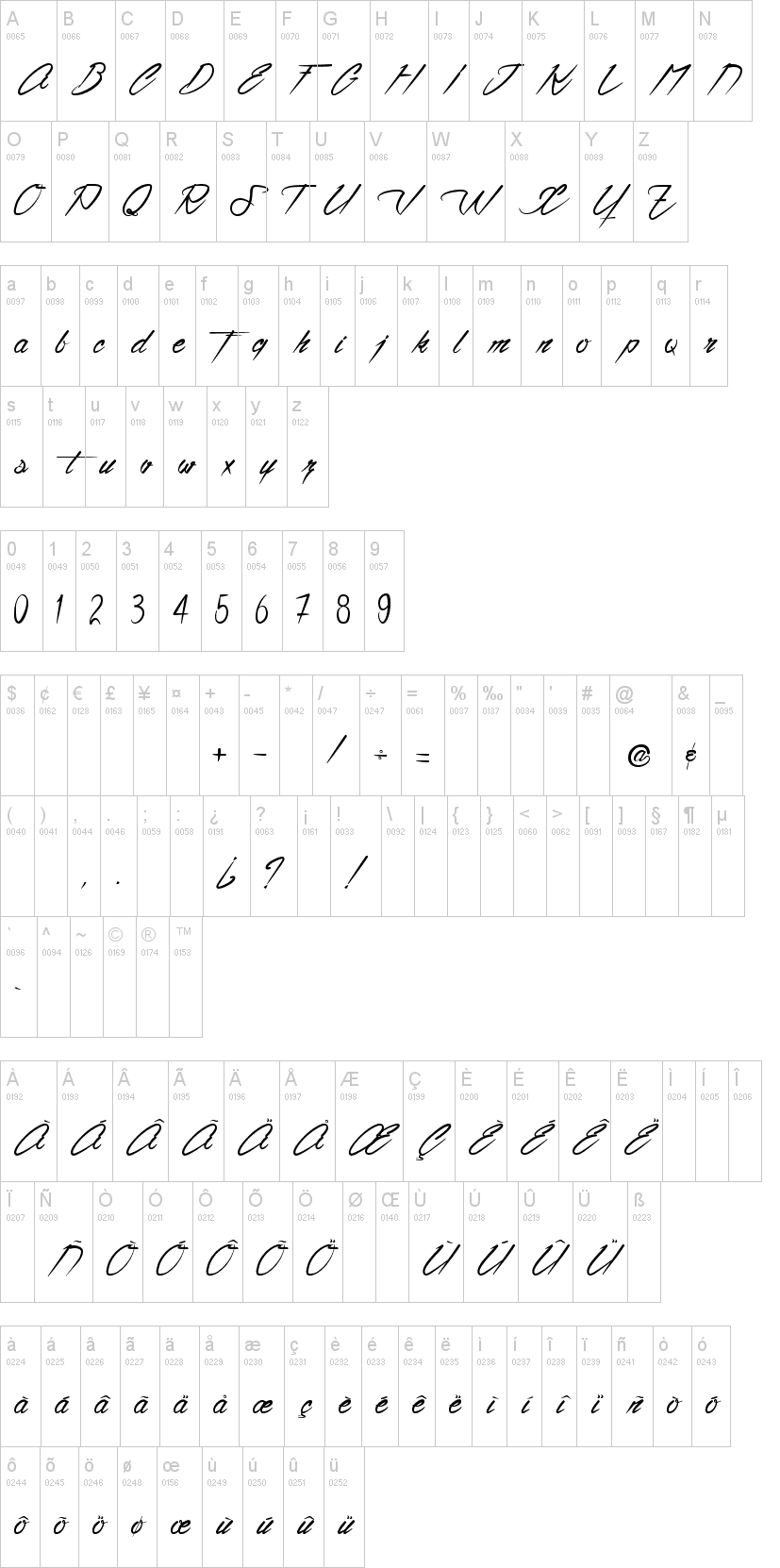
Ventilla Script 是一种优美的手写字体,其风格带有浪漫和女性化的气息。该字体由 Tama Putra 设计,于 2017 年首次发布。 Ventilla Script 字体的特点是流畅、优雅和可读性强。它的笔画流畅自然,仿佛用一支钢笔或毛笔写出来的一样。字母之间的间距适宜,大写字母更加优美,标点符号和数字也非常漂亮。 Ventilla Script 字体适用于各种场合,如品牌标志、宣传海报、婚礼贺卡、书籍封面等。因为它的风格典雅、温馨,非常适用于强调文字的情感和感性方面。而在商业方面,该字体可以增加产品或品牌的亲和力和信任感。 总之,Ventilla Script 是一种非常优美和实用的手写字体,具有很高的美感和可读性。内容介绍
Ventilla Script是一款非常不错的手写艺术字体,具有很好的视觉感,适合于文化类的宣传设计、商业类品牌的广告和产品包装设计以及个性化文字排版等较多场景。